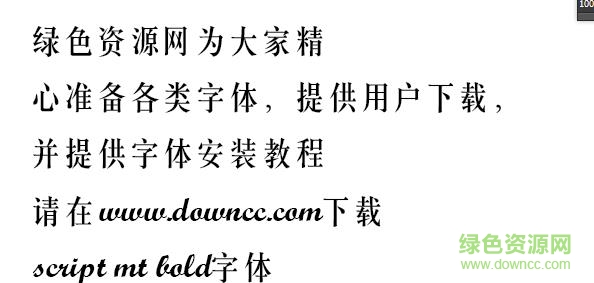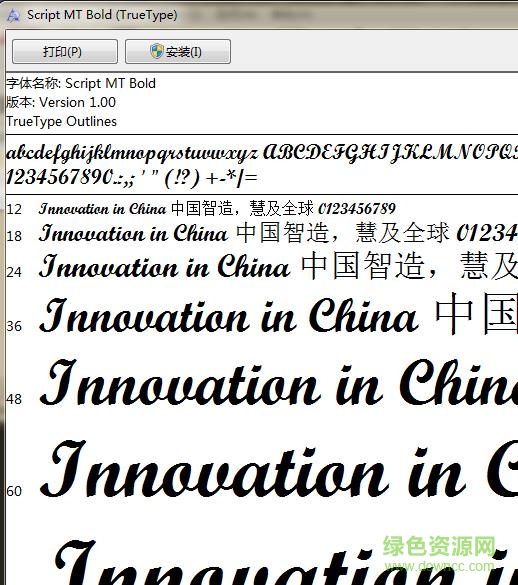
script mt bold英文字體ttf是一款練筆類型的字體樣式,通過將英文寫作方式實(shí)現(xiàn)練筆效果,讓你能夠感受到行云流水般的字體視覺體驗(yàn),十分不錯,你值得使用!
這款字體通過在字體的風(fēng)格上進(jìn)行了很大的變更讓你感受到不同于以往的英文字體樣式,用戶可以使用這款字體進(jìn)行眾多工作或者媒體制作!